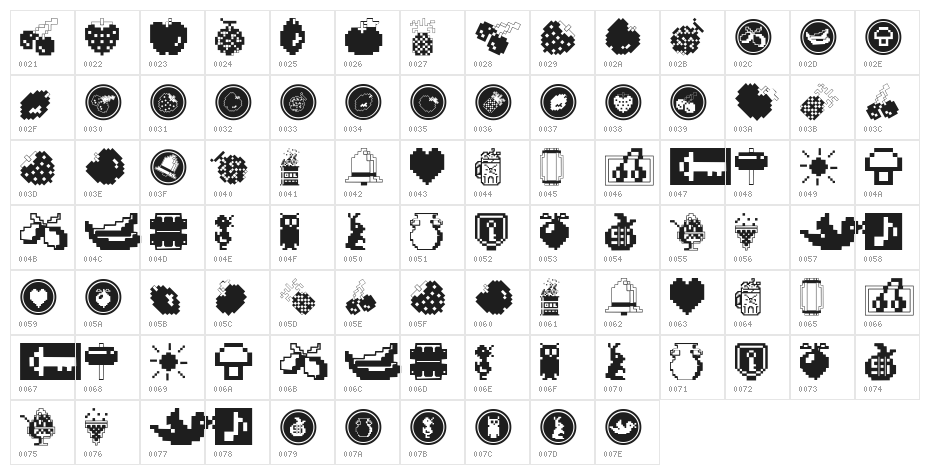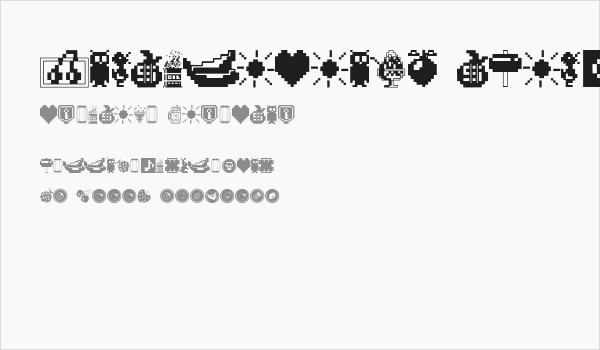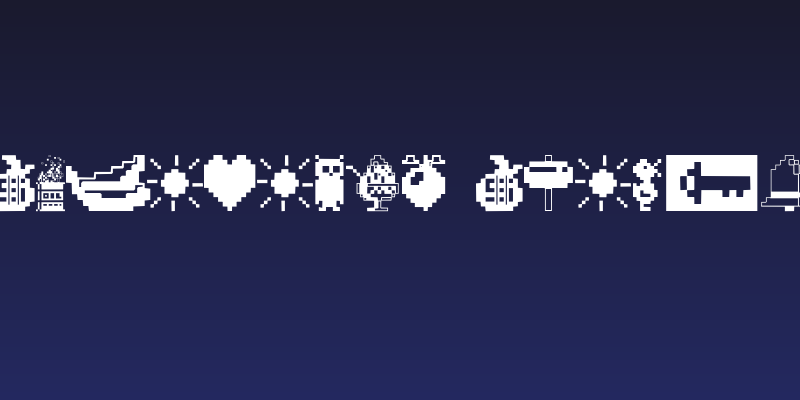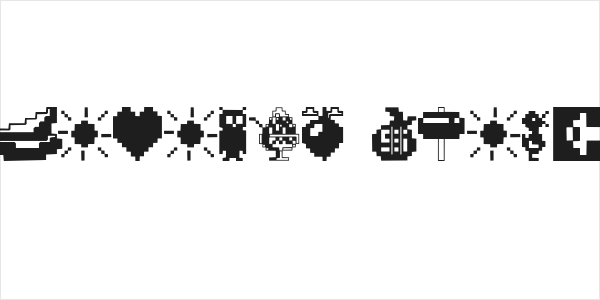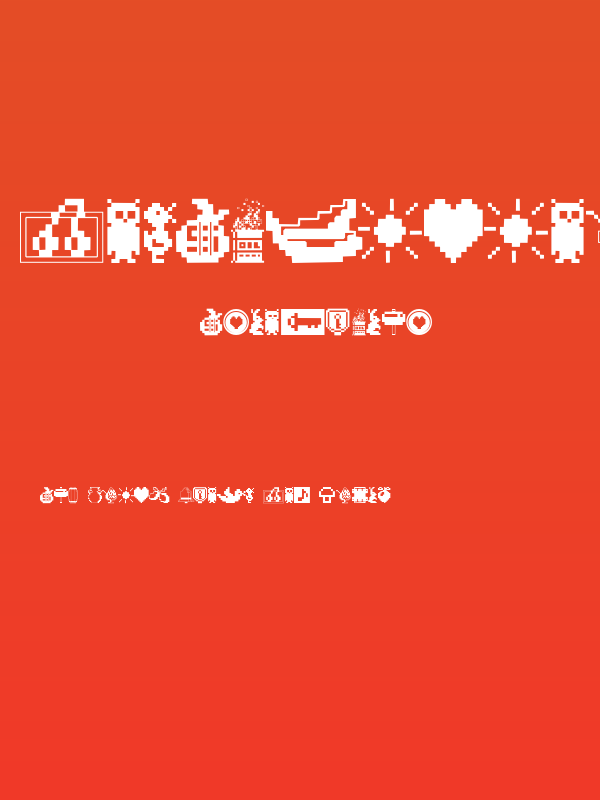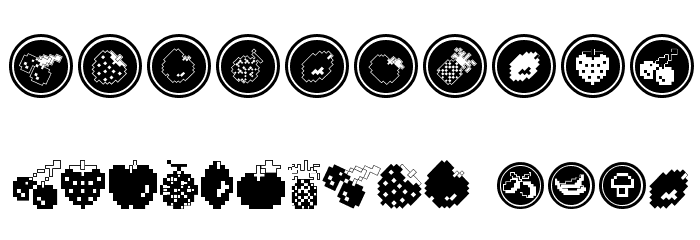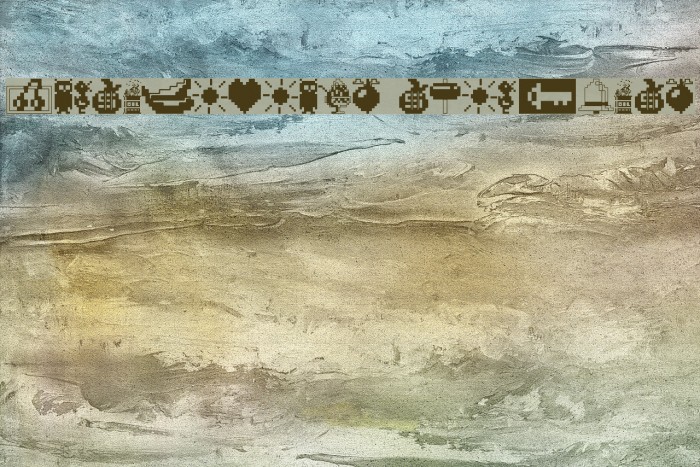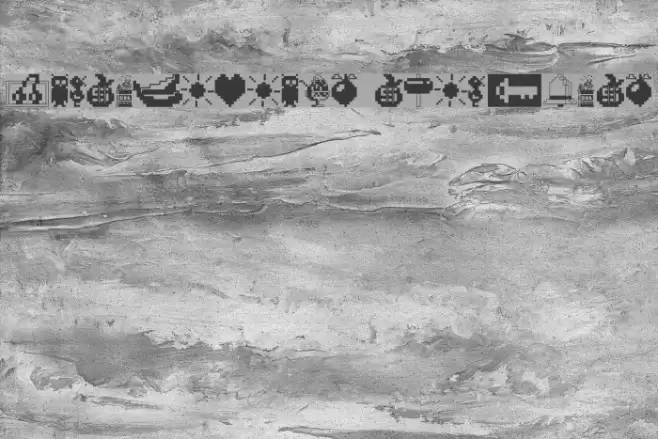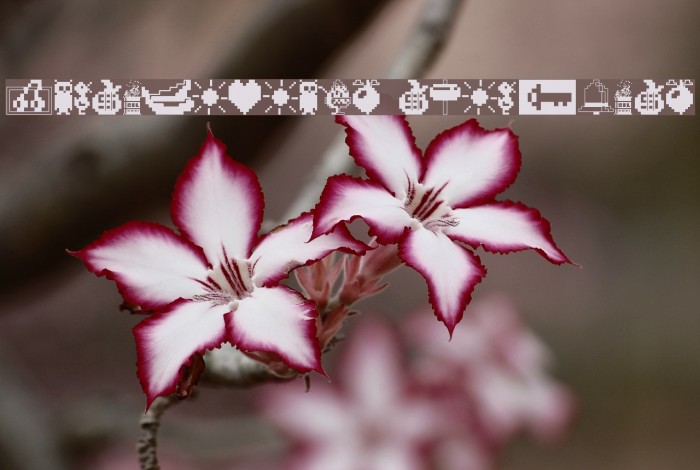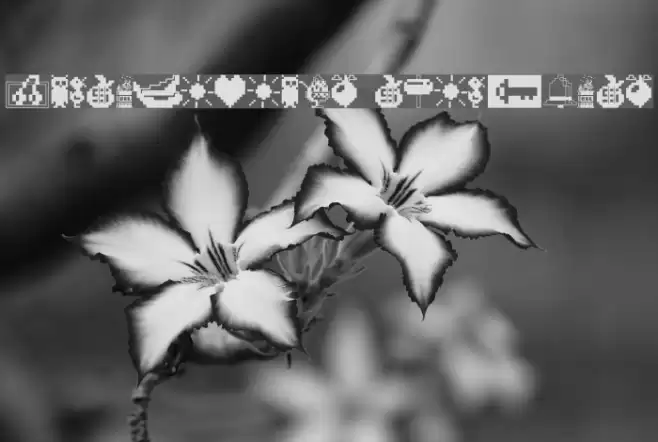
Fontalicious Thingbats Font
| Caso d'uso | Logos, Icons, Digital Art |
| Progetti proposti | Ideal for retro-themed video games, digital art projects, or nostalgic branding materials. |